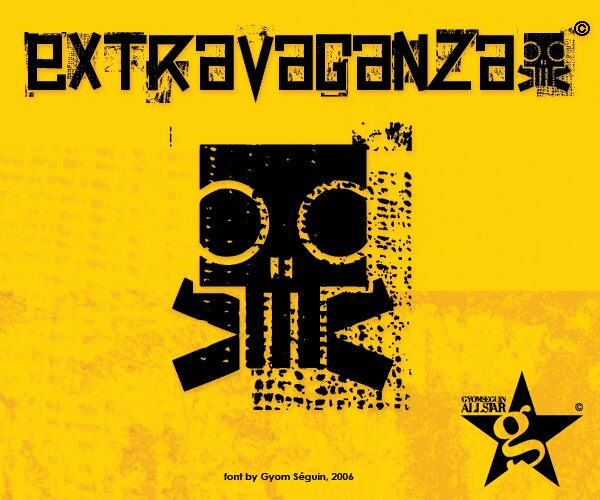
Extravaganza è un carattere display gratuito con un'estetica techno distorta. Forme pesanti a blocchi si scontrano con diagonali irregolari, mentre texture ruvide ed erose mangiano le lettere come il disturbo su uno schermo rotto. È un mix tra graffiti e glitch, con tratti spessi e carichi di inchiostro che colpiscono duramente, lasciando dietro di sé una scia di rumore digitale.
Usando Extravaganza, i tuoi titoli sembreranno usciti da un volantino rave o dal menu di un gioco distopico. Questo font gratuito brilla su poster di concerti, copertine di album, branding a tema hacker o cyber, grafiche streetwear e audaci titoli in motion graphics. Usalo in dimensioni grandi affinché i dettagli usurati siano ben leggibili e abbinalo a un semplice font sans serif geometrico per il testo di supporto, in modo da far risaltare il caos del lettering principale.